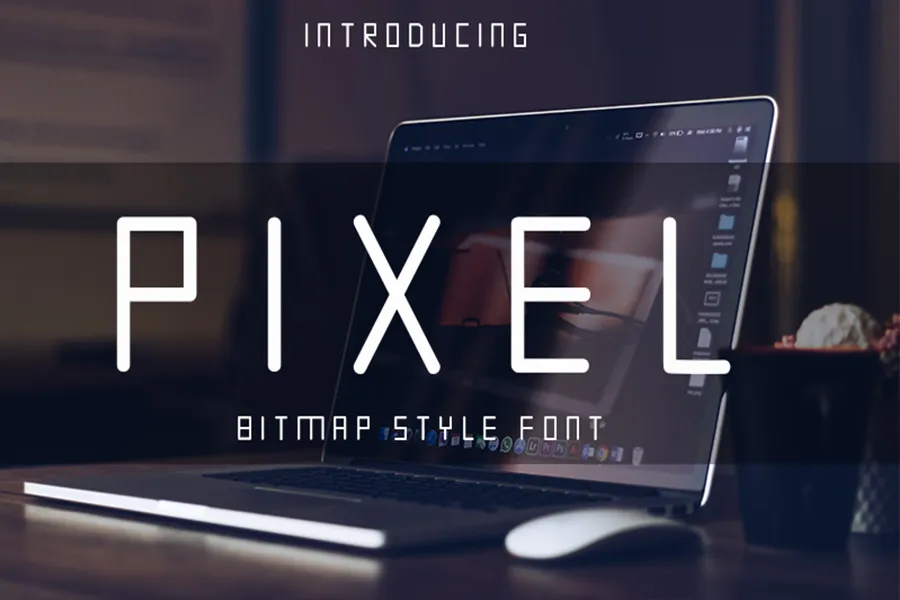
Pexel Font – Download Grátis
A Pexel Font é uma escolha inteligente para designers que buscam a essência clássica das serifas sem serem presos aos estilos antigos. Essa fonte continua com suas influências de sans-serif, mas se atualiza e se renova, mantendo sua elegância enquanto reflete um design contemporâneo e fresco. Suas capacidades versáteis vão desde cartões de visita até títulos e embalagens para estação ou diário pessoal, tornando-a uma opção ideal para ideias criativas em diversos formatos. Em suma, a Pexel Font oferece um equilíbrio harmonioso entre elegância clássica e uma presença moderna, garantindo que seja perfeita para qualquer projeto onde sua legibilidade e estética são importantes.